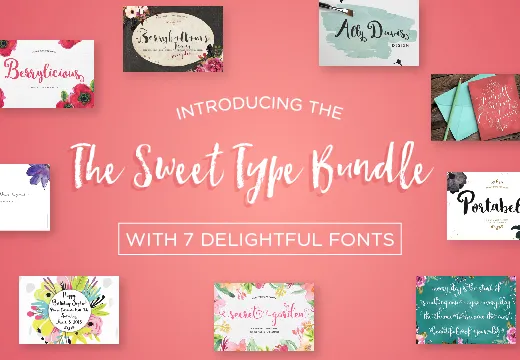
Идеальные шрифты для цитат и приглашений
Sweet Type Bundle — это набор из 7 современных и эстетически привлекательных шрифтов, собранных в единый пакет. Данный продукт предназначен для дизайнеров, оформителей и всех, кто работает с визуальным контентом и хочет придать своим проектам уникальный стиль. Набор включает в себя разнообразные начертания, от рукописных до каллиграфических и стильных скриптов, что позволяет использовать их для широкого спектра творческих задач.
• В состав пакета входят 7 уникальных шрифтов, подходящих для создания сложных и изысканных дизайн-проектов.
• Шрифты оптимизированы для создания качественной типографики, превращая обычный текст в художественный элемент оформления.